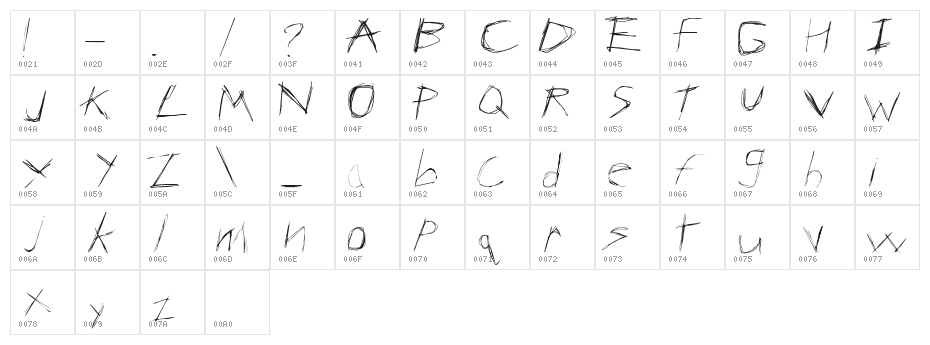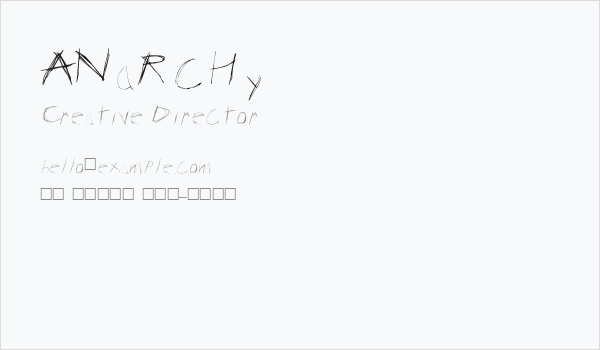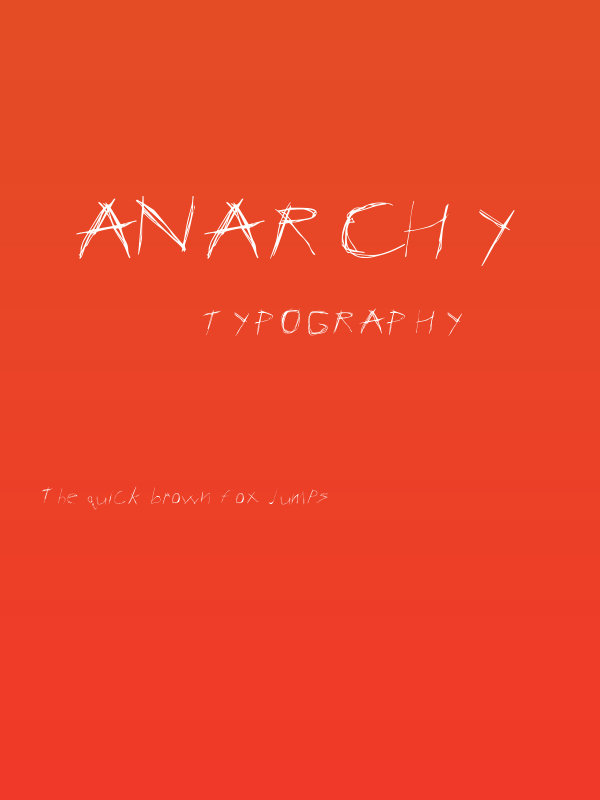
ANaRcHy Font
Font by SnatchSoft
| Gesamtstil | Edgy, Rebellious, Hand-drawn |
| Anwendungsfall | Headlines, Artistic projects, Branding |
| Vorgeschlagene Projekte | Ideal for punk-themed posters, album covers, graffiti art, and rebellious branding. |